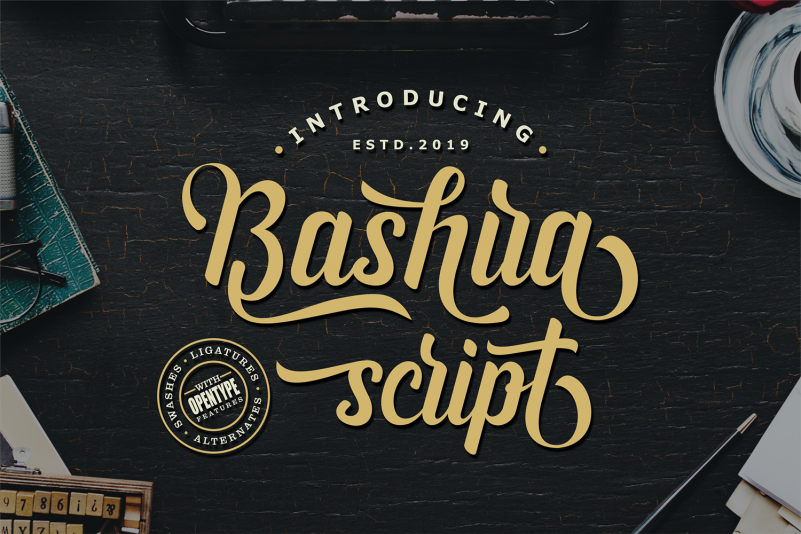
Bashira Script Font – Download Grátis
A Bashira Script Font é uma elegante escolha para designers e aficionados por tipos curiosos. Inspirada na natureza urbana e nas paisagens metropolitanas do Brasil, essa fonte script traz consigo uma atmosfera sofisticada e envolvente. Perfeita para aplicações onde o estilo e a personalidade são fundamentais — seja em design editorial, cartões de aniversário ou até mesmo como um toque de originalidade no design web —, a Bashira Script captura algo muito especial do nosso país. Com traços definidos e uma tipografia fluida, esta fonte oferece uma experiência visual que remete à diversidade cultural brasileira, ao mesmo tempo em que se encaixa perfeitamente na sua necessidade de gráficos únicos. Instale-a e deixe seu design brilhar com a graça e singularidade da Bashira Script Font.